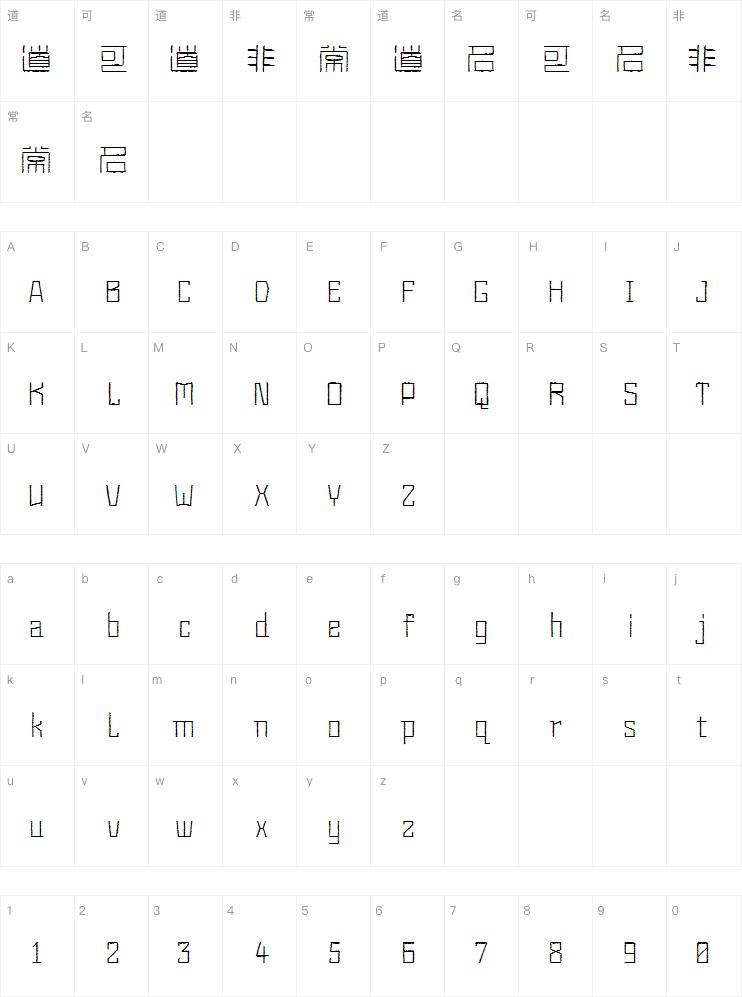
化圆为方,是谓方篆。汉仪方篆融合汉印缪篆的平方匀整、汉砖瓦当的朴拙浑厚以及铜镜铭的婉转流动,以现代设计手法重构传统金石文字,是篆书书写的一次创新尝试。字形端稳周正,笔画平直有力,线条可见金石刀笔的刚健遒劲,毛笔书写的质感正如篆印呈现于纸面。这款缪篆风格的书写字体气质古朴,适合传统文化艺术和文博文旅等应用场景。